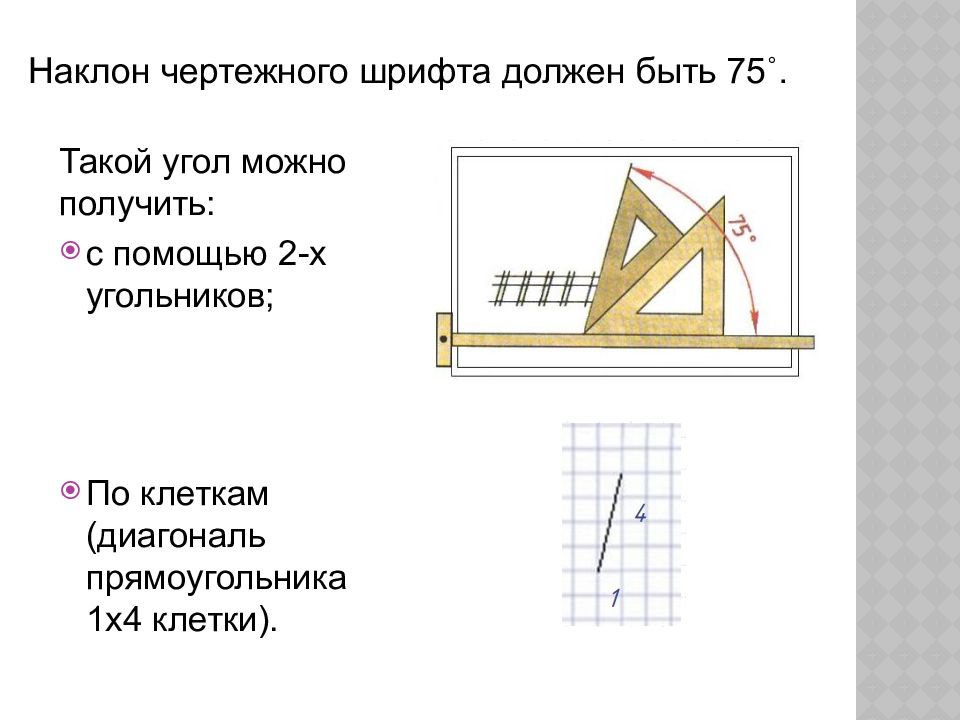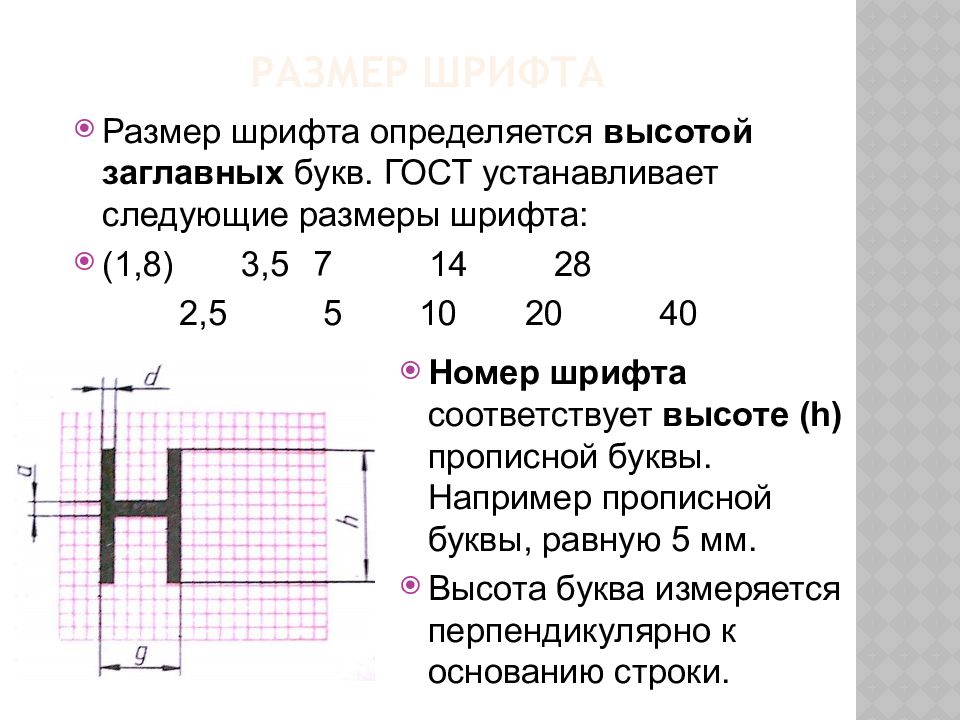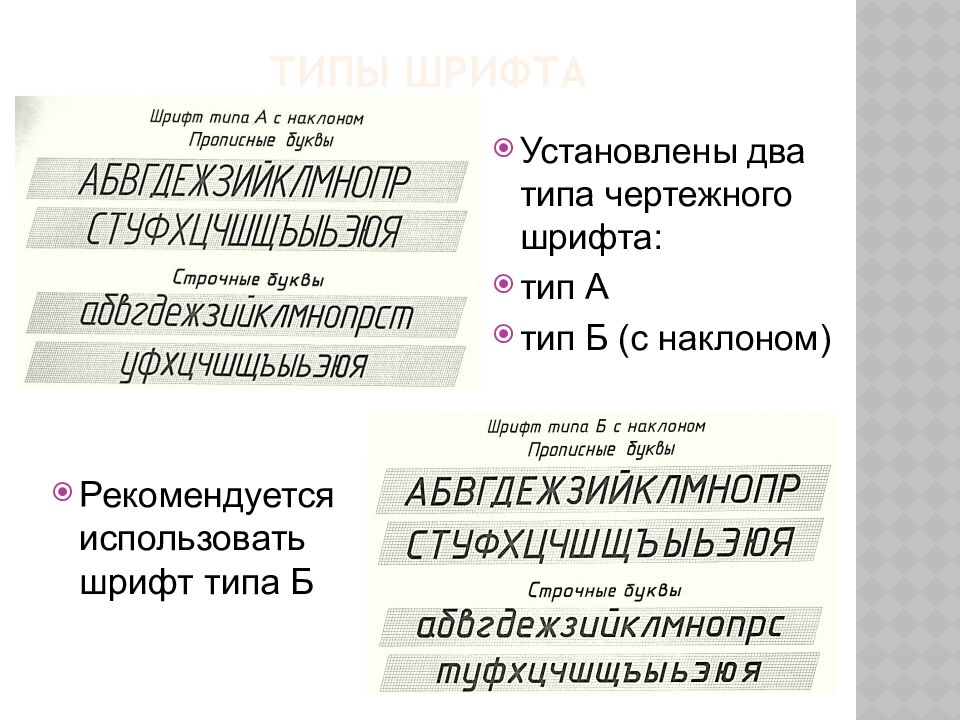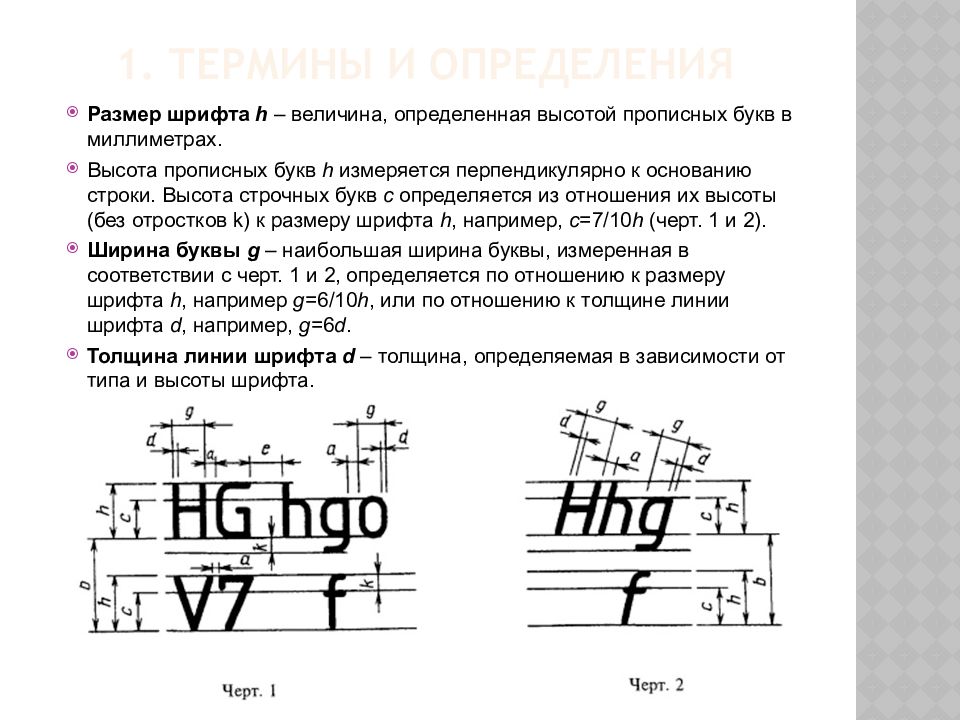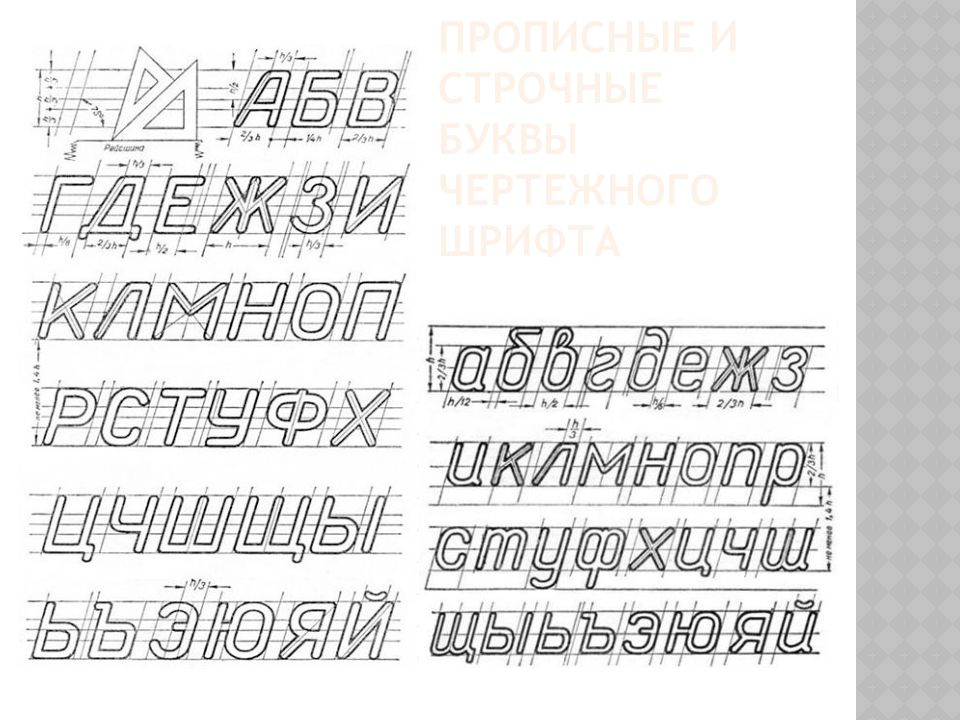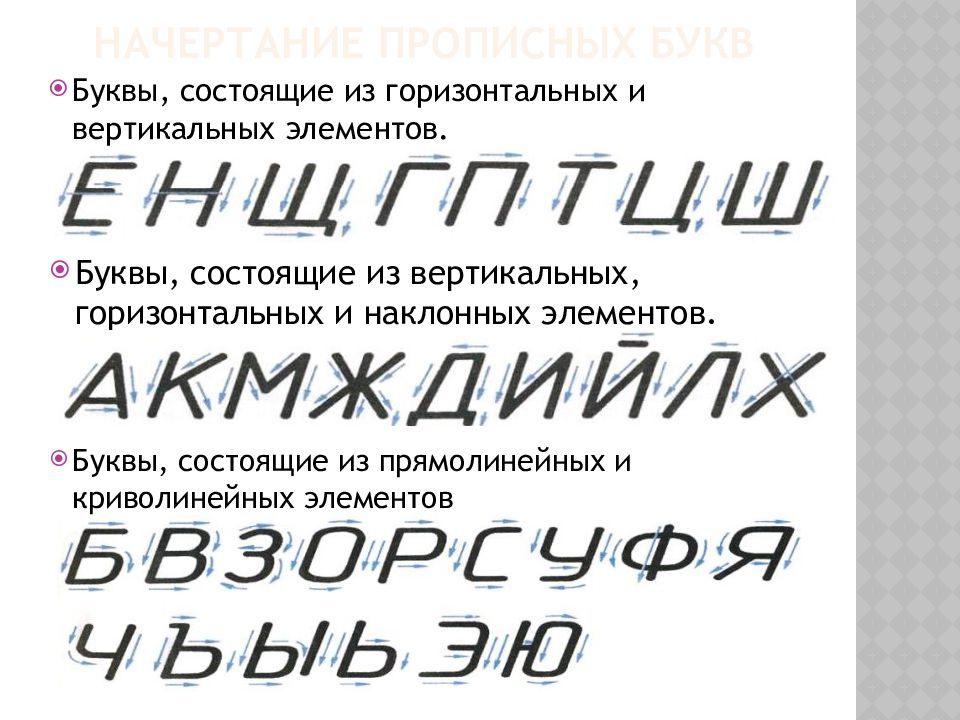
Первый слайд презентации: Общие правила оформления чертежей Шрифты чертежные
Слайд 3: 1. Термины и определения
Размер шрифта h – величина, определенная высотой прописных букв в миллиметрах. Высота прописных букв h измеряется перпендикулярно к основанию строки. Высота строчных букв с определяется из отношения их высоты (без отростков k ) к размеру шрифта h, например, с =7/10 h (черт. 1 и 2). Ширина буквы g – наибольшая ширина буквы, измеренная в соответствии с черт. 1 и 2, определяется по отношению к размеру шрифта h, например g =6/10 h, или по отношению к толщине линии шрифта d, например, g =6 d. Толщина линии шрифта d – толщина, определяемая в зависимости от типа и высоты шрифта.
Слайд 4: Шрифт чертежный ГОСТ 2.304-81
Шрифт – это начертание букв какого-либо алфавита, цифр и знаков. Требования: должны быстро выполняться, легко чертиться и давать хороший отпечаток при размножении чертежей. Первый стандарт «Шрифты для надписей» был разработан и утвержден в 1919 г. Стандарт устанавливает и определяет высоту и ширину букв и цифр, толщину линии обводки, расстояние между буквами, словами, строками.
Слайд 5: Типы шрифта
Рекомендуется использовать шрифт типа Б Установлены два типа чертежного шрифта: тип А тип Б (с наклоном)
Слайд 6
Наклон чертежного шрифта должен быть 75˚. Такой угол можно получить: с помощью 2-х угольников; По клеткам (диагональ прямоугольника 1х4 клетки).
Слайд 7: Размер шрифта
Номер шрифта соответствует высоте ( h ) прописной буквы. Например прописной буквы, равную 5 мм. Высота буква измеряется перпендикулярно к основанию строки. Размер шрифта определяется высотой заглавных букв. ГОСТ устанавливает следующие размеры шрифта: (1,8) 3,5 7 14 28 2,5 5 10 20 40
Слайд 8: Начертание прописных букв
Буквы, состоящие из горизонтальных и вертикальных элементов. Буквы, состоящие из вертикальных, горизонтальных и наклонных элементов. Буквы, состоящие из прямолинейных и криволинейных элементов